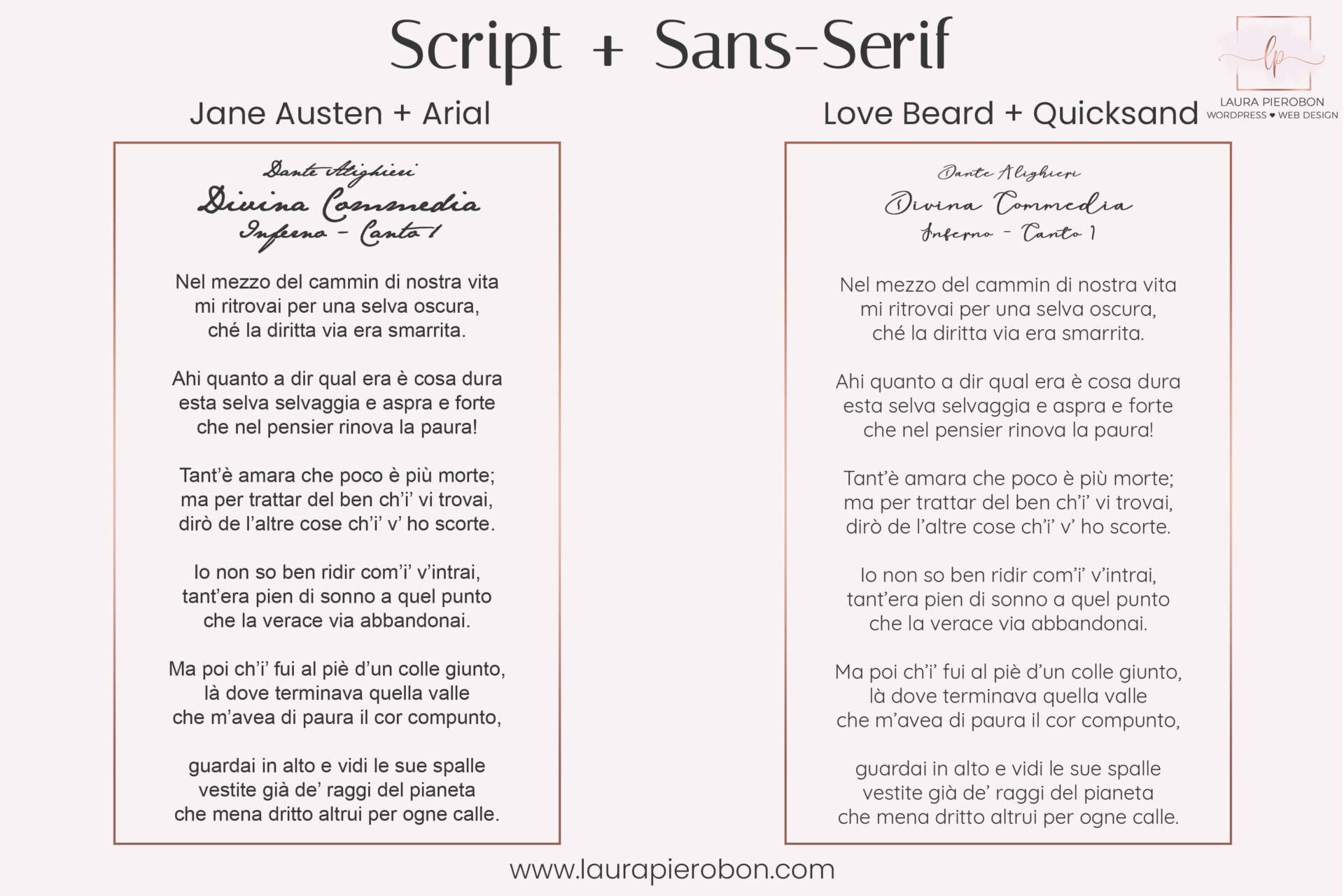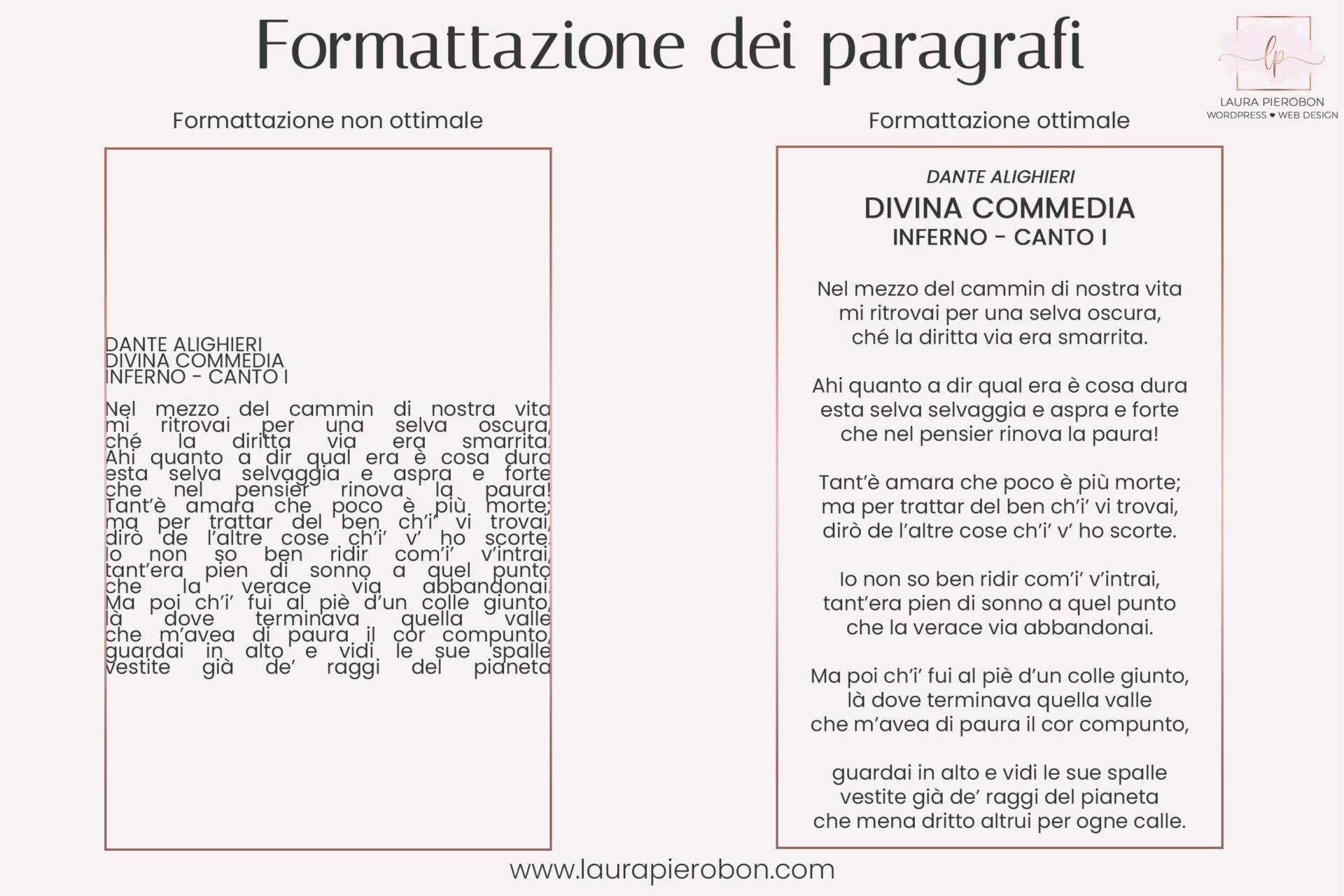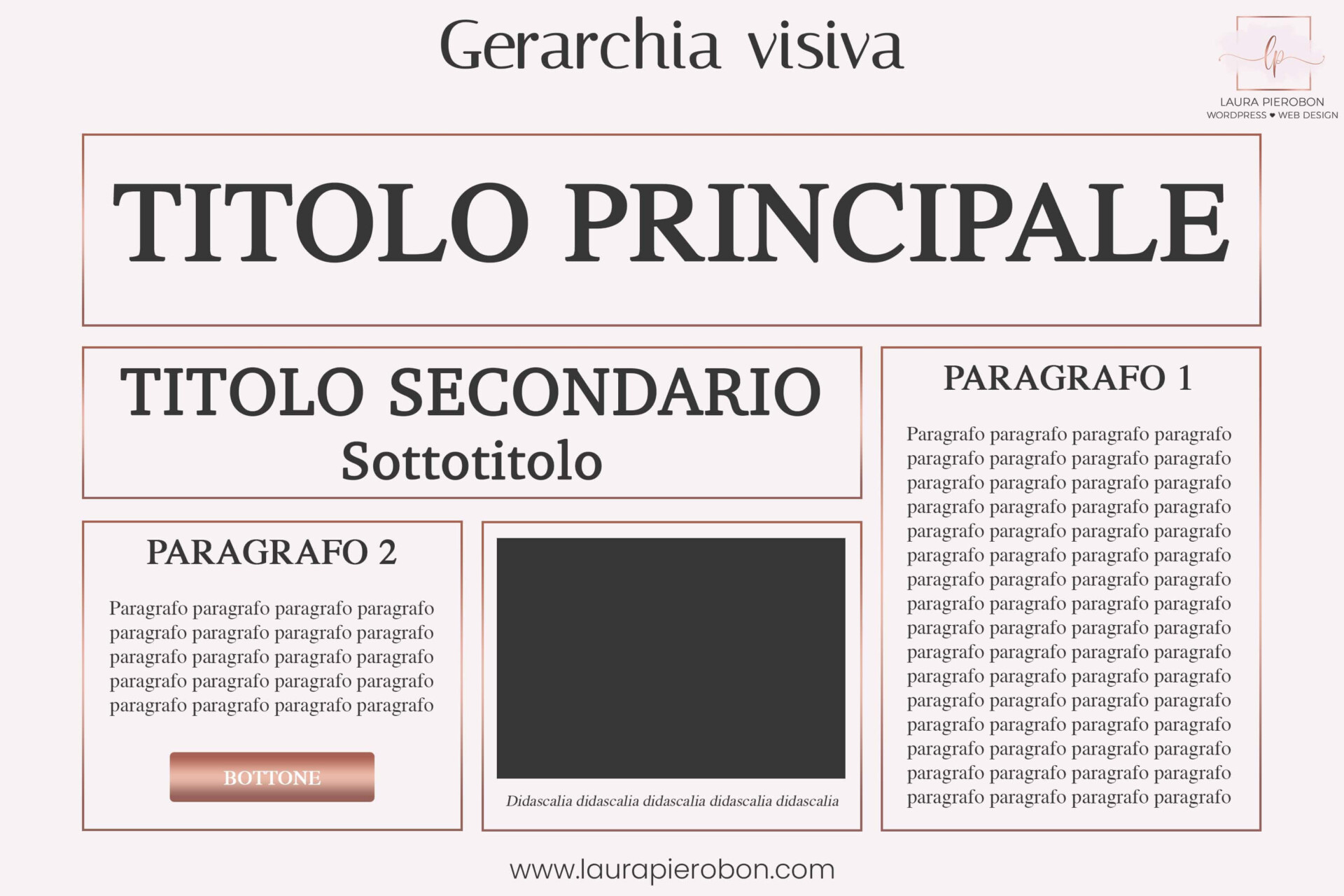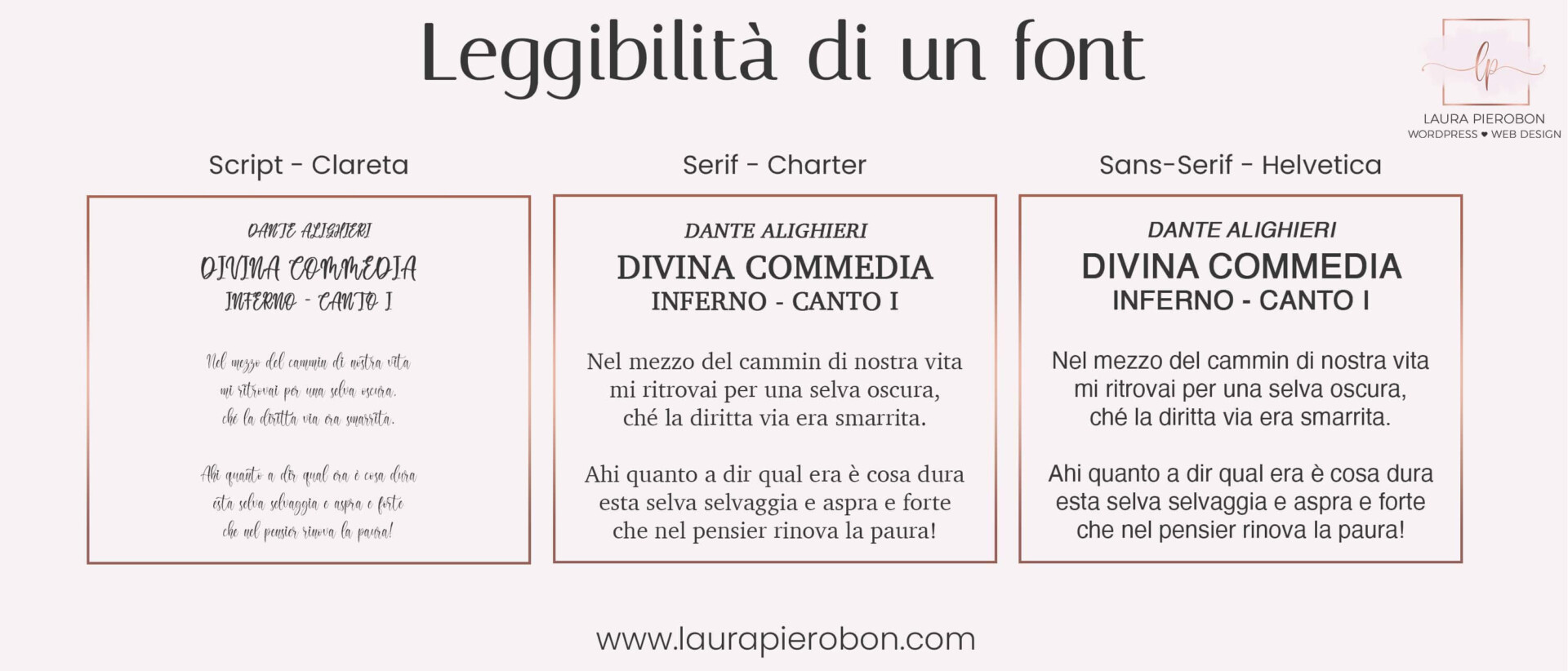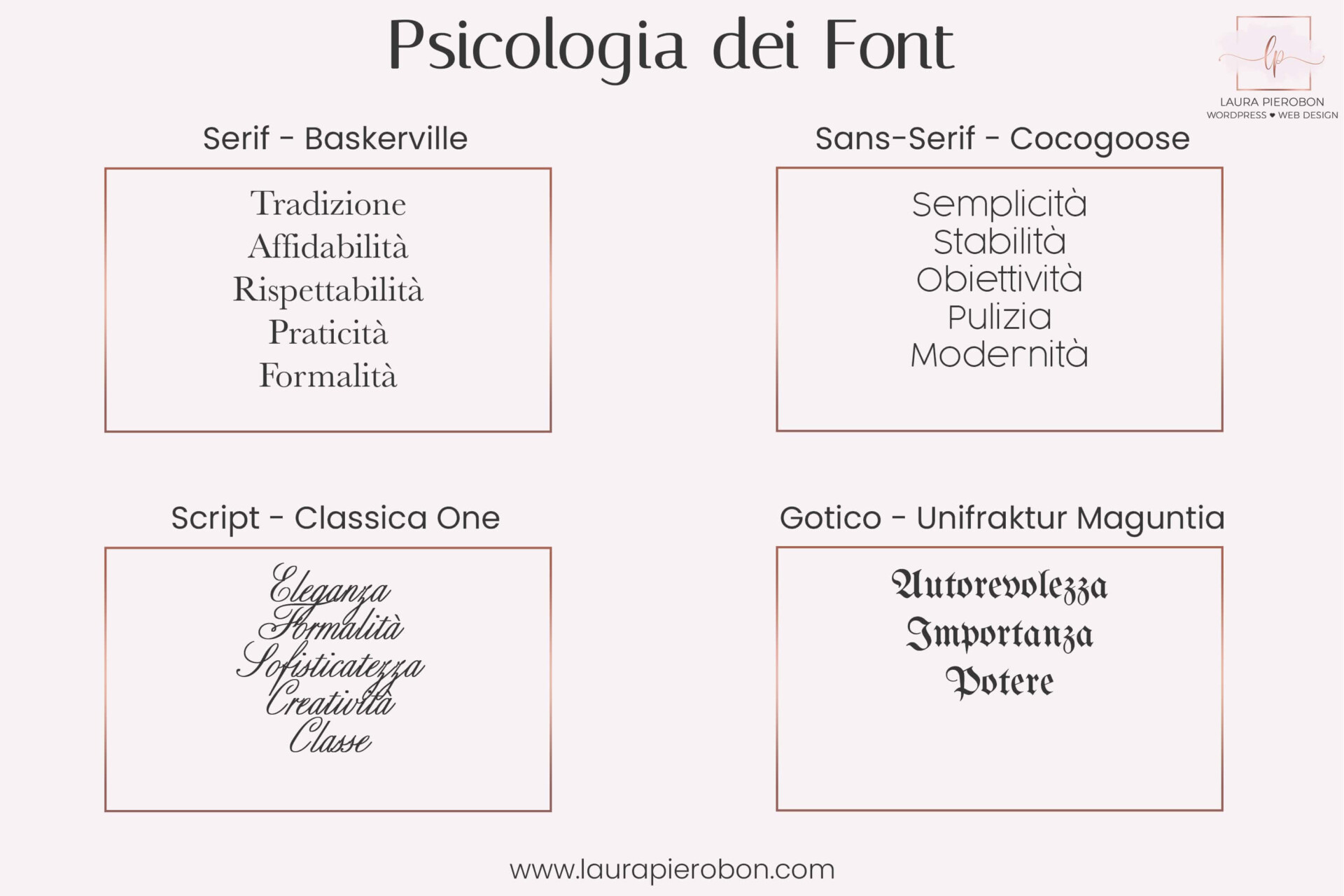
Ora che abbiamo visto cos’è un Font e come si compone, impariamo come scegliere e abbinare i font tra loro.
Come scegliere il giusto font
Nel momento in cui dobbiamo scegliere quale font utilizzare per il nostro progetto, sia esso un logo, un sito o una stampa, esistono vari aspetti oggettivi, estetici e psicologici di cui tenere conto.
Leggibilità
Il primo aspetto fondamentale nella scelta di un font è la leggibilità. Per poter essere compreso, un testo deve essere leggibile.
Font calligrafici e decorativi attraggono l’attenzione del lettore e quindi sono perfetti da utilizzare, ad esempio, in un titolo o in una breve scritta. Tuttavia non hanno una buona leggibilità rispetto a font più semplici come il Serif o il Sans-Serif che vanno invece preferiti nel caso di testi più lunghi e discorsivi.
La leggibilità di un testo non è data solo dalla scelta del font, ma anche dalla sua formattazione. È quindi altrettanto importante tenere conto della suddivisione e della giustificazione dei paragrafi, del corretto uso dell’interlinea e dell’utilizzo dei vari stili e dimensioni, il tutto per creare una certa dinamicità che aiuti l’utente a proseguire con la lettura.
Psicologia dei Font
Esattamente come per i colori, anche i font hanno un loro aspetto psicologico. Sapere quali sensazioni ed emozioni trasmettono può aiutare a far passare un determinato messaggio.
Ad esempio, se stiamo creando un logo per uno studio legale molto probabilmente vorremmo trasmettere un’idea di autorevolezza, affidabilità e rispettabilità.
Ogni famiglia di font suscita sensazioni diverse e per questo esistono font che si adattano meglio a certi scopi rispetto ad altri:
- I font Serif trasmettono un’idea di Tradizione, Affidabilità, Rispettabilità, Praticità e Formalità. Sono di facile lettura e per questo vengono tradizionalmente usati nella stampa cartacea, come libri e giornali.
- I font Sans-Serif danno invece una sensazione di Semplicità, Stabilità e Obiettività. È uno stile molto pulito e moderno e facilmente leggibile. Si usano spesso nei loghi e nei testi per il web.
- I font Script e calligrafici sono Eleganti, Formali e Sofisticati e rendono l’idea di qualcosa di creativo e di classe, per questo sono spesso usati negli inviti formali (ad esempio per un matrimonio o un evento importante) e nei loghi.
- I font Gotici trasmettono una sorta di Autorevolezza, Importanza e Potere. Se ne possono vedere degli esempi nei nomi di alcune testate giornalistiche. In genere, oggigiorno vengono usati solo per scopi decorativi.
Come abbinare i font
Quando ci troviamo davanti all’esigenza di combinare vari font tra loro ci sono alcune regole di base che dovremmo seguire.
1. Stabilire una gerarchia visiva
Prima di tutto dobbiamo capire esattamente quanti font dovremo utilizzare e per quale funzione. Facciamo un elenco delle varie porzioni di testo che andranno a comporre il nostro progetto, come ad esempio titoli, corpo del testo, didascalie, bottoni, pulsanti, eccetera. Dopodiché, in base al tipo di progetto che stiamo realizzando, stabiliamo quanta importanza dovrà avere ogni singola porzione di testo: ad esempio, un titolo sarà più rilevante di una didascalia, mentre un bottone probabilmente dovrà catturare di più l’attenzione rispetto al corpo del testo e così via.
Creare una gerarchia visiva aiuta a rendere più chiaro il messaggio che vogliamo trasmettere ponendo l’enfasi sulle parti più importanti.
2. Usare pochi font
Anche in questo caso, come per i colori, meno è meglio. Usare troppi font crea confusione. Meglio limitarsi ad usarne solo due o massimo tre. Il testo sarà molto più leggibile e il messaggio passerà in modo più chiaro.
3. Creare contrasto
Il contrasto aiuta a creare quella dinamicità nel testo che lo rende più facilmente leggibile. Per questo non è una buona idea usare font troppo simili tra loro perché il rischio che si corre è quello di appiattire troppo il testo e renderlo così più difficile e noioso da leggere.
Nel caso in cui si voglia utilizzare solo un certo tipo di font, si può creare contrasto giocando con i pesi e le dimensioni del testo.
Esempi di combinazioni che funzionano
Una delle combinazioni più classiche ed utilizzate è quella tra i font Serif e Sans-Serif. Combinare questi due font tra loro permette di creare un testo dinamico ma comunque facilmente leggibile.
Anche la combinazione tra font Script e Sans-Serif funziona bene. Questo abbinamento dà l’idea di qualcosa di elegante e raffinato.
Combinando un font Script con un font Serif si ottiene un effetto ancora più elegante e di classe.
Strumenti utili
Se volete provare a giocare un po’ con i font per trovare la combinazione perfetta per il vostro progetto, vi consiglio alcuni tool online che vi possono tornare utili:
Canva Font combinations
È uno strumento molto pratico e semplice da usare che permette di trovare la combinazione di font che meglio si abbinano tra loro. Basterà selezionare dal menu a tendina un font primario e Canva vi proporrà alcuni abbinamenti tra cui scegliere quello che più si adatta alle vostre esigenze.
Typ.io
Typ.io non è un tool per generare combinazioni di font, ma mette a disposizione una raccolta di esempi che seguono i trend del momento. È anche possibile ricercare gli abbinamenti di un font in particolare semplicemente digitandone il nome nella barra di ricerca.
Google Fonts
La libreria di Google contente migliaia di font gratuiti che puoi scaricare e utilizzare per i tuoi progetti.